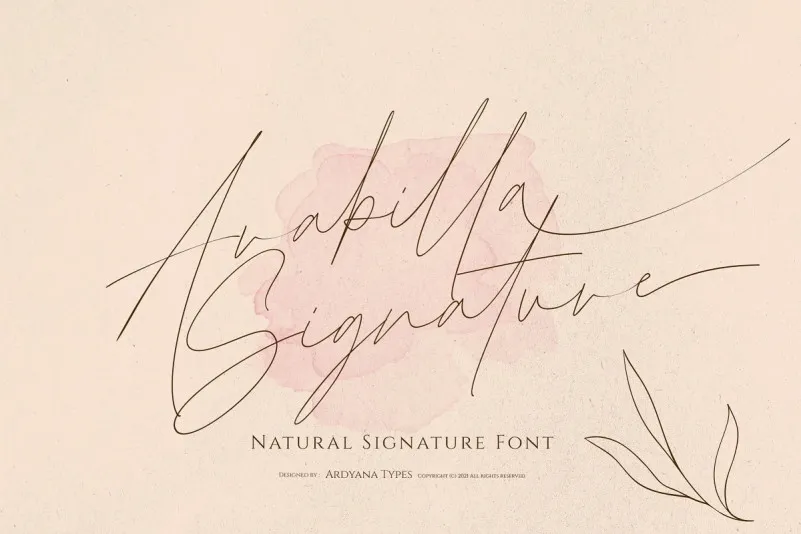
A Arabilla Signature Font é uma elegante tipografia script com um estilo de assinatura feminino. Com feições suaves e delicadas, esta fonte cativa os olhos por onde passa. Desenvolvida pelo designer Ardyanatypes, a Arabilla possui um charme incomparável que torna-a perfeita para diversos projetos gráficos em seu estilo: desde as convidativas cartas de negócios até as encantadoras invitaciones de casamento; da arte criativa e flirty à design atrativo de produtos. Suas linhas sutis fazem dela uma escolha ideal para aplicar um toque delicado em qualquer projeto, seja para publicidade, embalagens ou até mesmo watermark. A Arabilla é a fonte perfeita para quem busca incorporar uma sensação natural e elegante aos seus projetos de design.